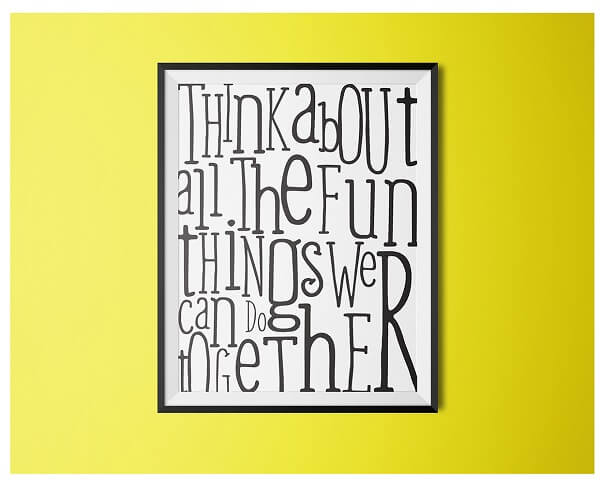
手書きだけどクール!オフィシャルなシーンでも使える英字フリーフォント「Weem」が新鮮!
手書き風の英字フォントと言うと、「柔らかさ」や「親しみやすさ」の印象が先立ち、やや軽いものが多いように感じることはありませんか?また手書きとなると筆記体のものが多いですが、ハッキリ言って日本人にとって筆記体で書かれた英文はあまり読みやすいものではありませんよね。
そんなこともあり手書き風のフォントを企業の公式サイトの見出しで使うのは結構勇気のいる選択だと思いますが、あえてそのシリアスな場面の見出しで使われることを意図してデザインされたブロック体の手書き風英字フォントがこちらの「Weem」です。
こちらの「Weem」はメールアドレスの登録だけでダウンロードできるフリーフォントですが英数字と句読点だけではありません。英語以外の言語にも対応できるようアクセント記号、ウムラウト記号なども使用することができます。
実際にこの「Weem」がメインで使われているシーンは下画像です。
手書きフォントですが、柔らかすぎず、軽すぎないほどよいクールさを演出することもできそうですね!